Font tulisan tangan, atau handwriting adalah jenis font yang meniru gaya tulisan manusia. Font ini mencakup berbagai gaya tulisan, mulai dari yang terbaca jelas hingga yang lebih dekoratif. Di kalangan desainer grafis, font tulisan tangan sering digunakan untuk memberikan sentuhan personal pada desain mereka.
Popularitas font tulisan tangan pun terus meningkat seiring dengan permintaan akan desain yang lebih individual dan kreatif, termasuk kartu ucapan, undangan, poster, logo, dan banyak lagi. Kehadiran font tulisan tangan memberikan nuansa yang hangat, ramah, dan mengundang interaksi yang lebih dekat antara pesan yang ingin disampaikan dengan audiensnya. Nah, dalam artikel ini, kami menyediakan 40 font tulisan tangan terbaik yang dapat Anda unduh dan gunakan secara gratis! Yuk, simak daftarnya di bawah ini!
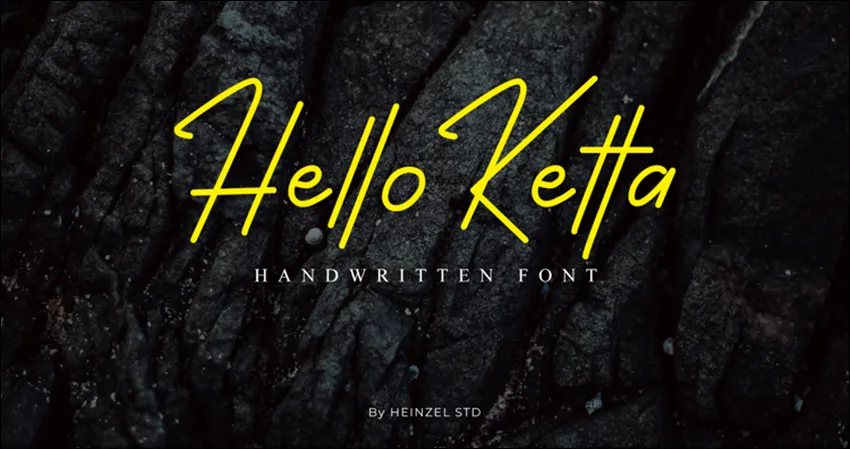
Font pertama adalah Hello Ketta. Font ini memiliki desain yang fresh dan elegan, cocok digunakan untuk proyek desain kartu ucapan, poster, dan masih banyak lagi.
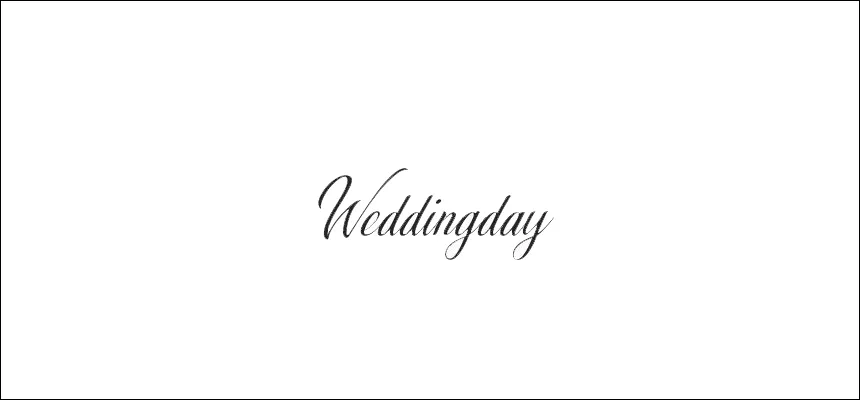
Font kedua adalah Weddingday. Font ini memiliki gaya kursif dengan sentuhan yang elegan dan romantis, ideal digunakan untuk undangan pernikahan atau materi-materi yang berkaitan dengan acara pernikahan untuk memberikan kesan yang romantis, mewah dan berkelas.
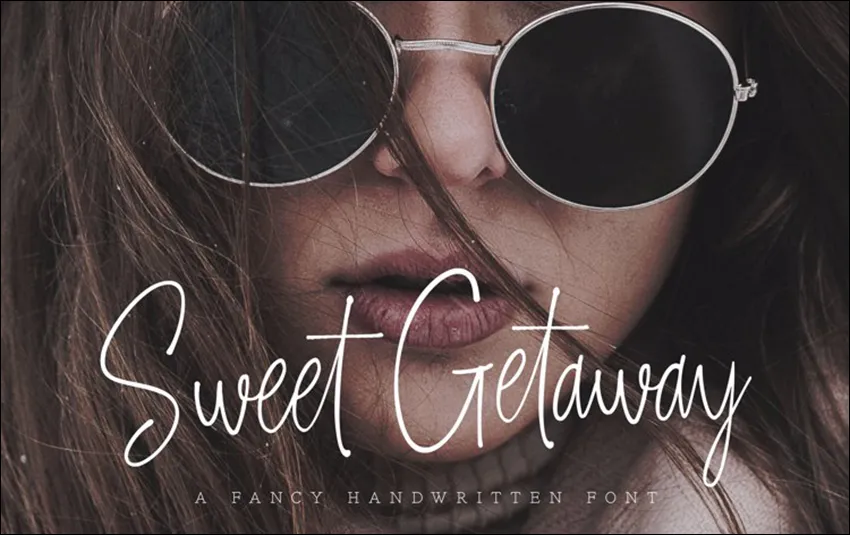
Selanjutnya adalah font Sweet Getaway. Dengan gaya kursif dan desain yang casual, font ini cocok digunakan untuk proyek-proyek yang ingin menampilkan suasana liburan atau petualangan, seperti scrapbook atau postingan media sosial tentang traveling.
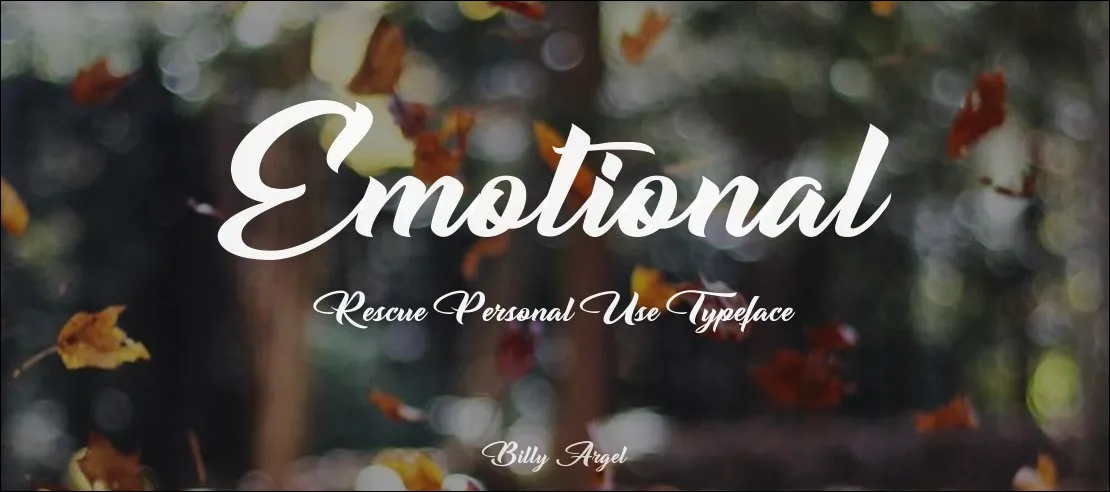
Font ini memiliki desain kursif yang bold dan artistik. Cocok digunakan untuk proyek-proyek kreatif yang ingin mengekspresikan emosi atau perasaan, seperti kartu ucapan, undangan, poster, dan lain-lain.
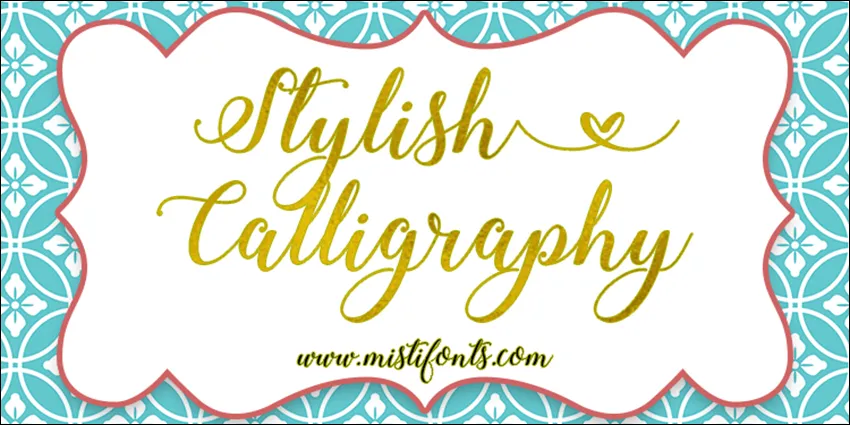
Dengan desain kaligrafi yang anggun dan elegan, font ini cocok digunakan untuk berbagai macam proyek desain, mulai dari kartu undangan, cover buku, banner, branding, logo, dan lain-lain.
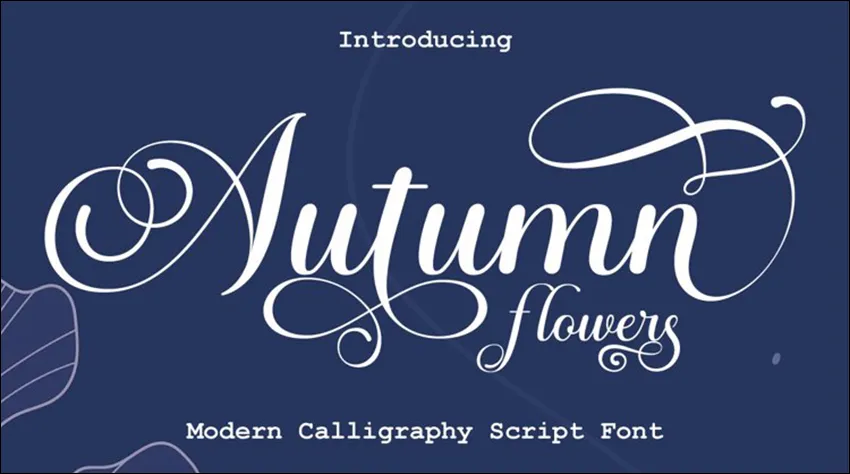
Font ini menghadirkan desain kaligrafi modern yang lembut dan elegan, cocok digunakan untuk proyek desain kartu ucapan, poster, undangan, dan masih banyak lagi.
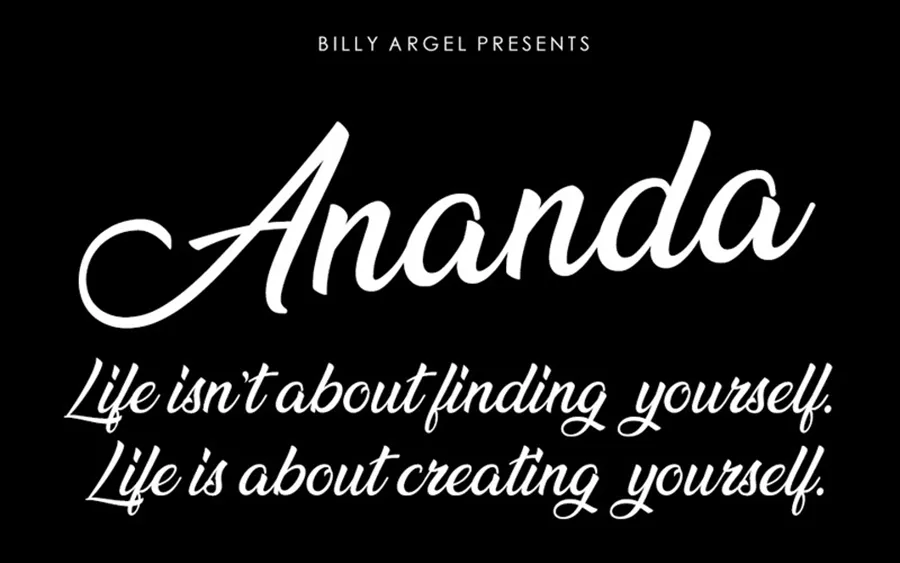
Dengan desain kursif bold dan artistik, font ini cocok untuk proyek-proyek yang ingin menonjolkan pesan atau teks utama secara dramatis. Digunakan untuk judul, slogan, atau desain yang ingin menampilkan kesan yang kuat dan menarik perhatian.
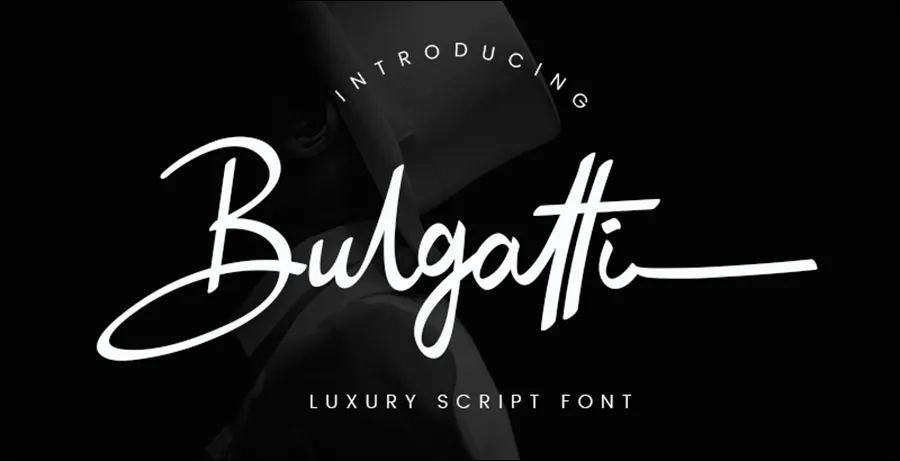
Font ini memiliki tampilan retro yang bersih, cocok untuk proyek desain yang membutuhkan kesan yang profesional dan terorganisir. Kegunaannya bisa untuk desain logo, materi promosi, atau materi perusahaan yang ingin menampilkan kesan yang modern dan terstruktur.
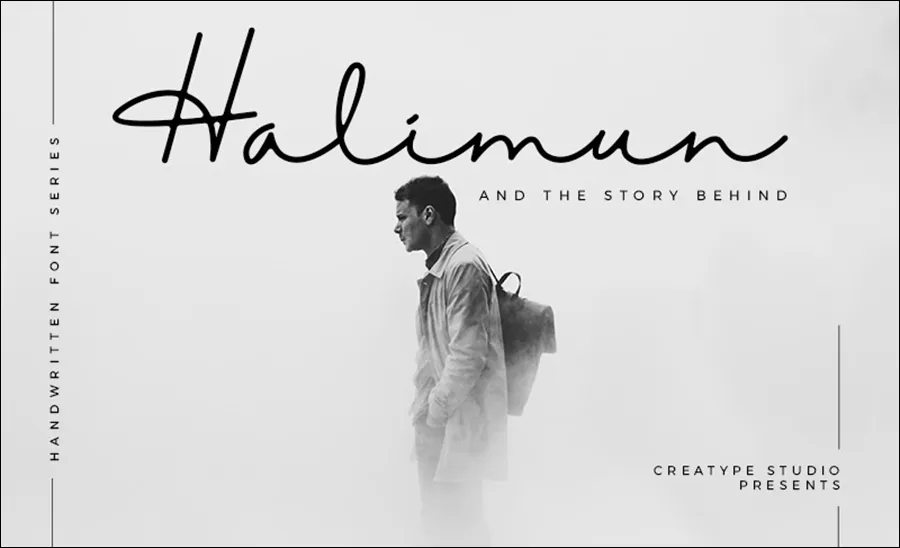
Dengan desain vintage modern, font ini cocok untuk proyek-proyek desain kartu ucapan, poster, book cover, atau desain yang ingin menampilkan keindahan dan kelembutan.
Font ini memiliki gaya tulisan tangan retro tahun 1970an, cocok untuk proyek-proyek desain yang membutuhkan sentuhan personal dan artistik, seperti poster, banner, label, atau lainnya.
Dengan desain kursif modern, font serif pendek ini cocok digunakan untuk proyek-proyek desain logo, branding, pengemasan, dan lain-lain.
Font ini memiliki gaya yang artistik dan unik, cocok untuk proyek-proyek yang ingin menonjolkan kreativitas dan individualitas. Kegunaannya bisa untuk desain seni, poster, kartu ucapan, atau materi promosi yang ingin menampilkan kesan yang eksentrik dan unik.
Dengan desain yang casual dan modern, font ini cocok digunakan untuk proyek-proyek desain yang ingin menarik perhatian dan memberikan kesan santai, seperti desain kartu undangan pernikahan, hingga banner promosi, dan lain-lain.
Font sans-serif ini memiliki desain yang bersih dan modern, cocok digunakan untuk proyek-proyek yang ingin menyampaikan pesan dengan jelas dan tegas, seperti presentasi, buku panduan, dan lain sebagainya.
Dengan desain kursif modern dan nuansa girly, font ini cocok digunakan untuk proyek-proyek yang ingin menampilkan keceriaan dan optimisme, seperti kartu ucapan, poster, banner, dan masih banyak lagi.
Font ini memiliki perpaduan desain kaligrafi modern dan retro, cocok digunakan untuk proyek-proyek desain kartu undangan, logo, poster, branding, atau lainnya.